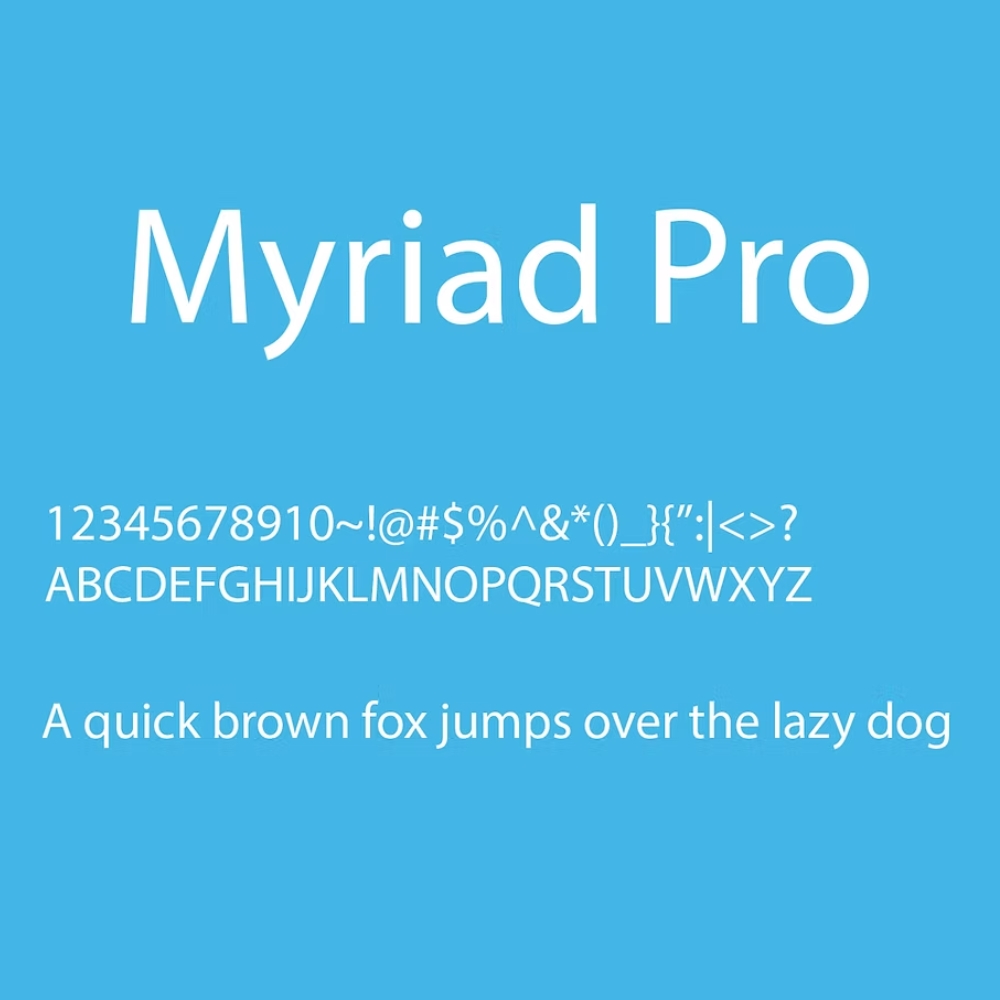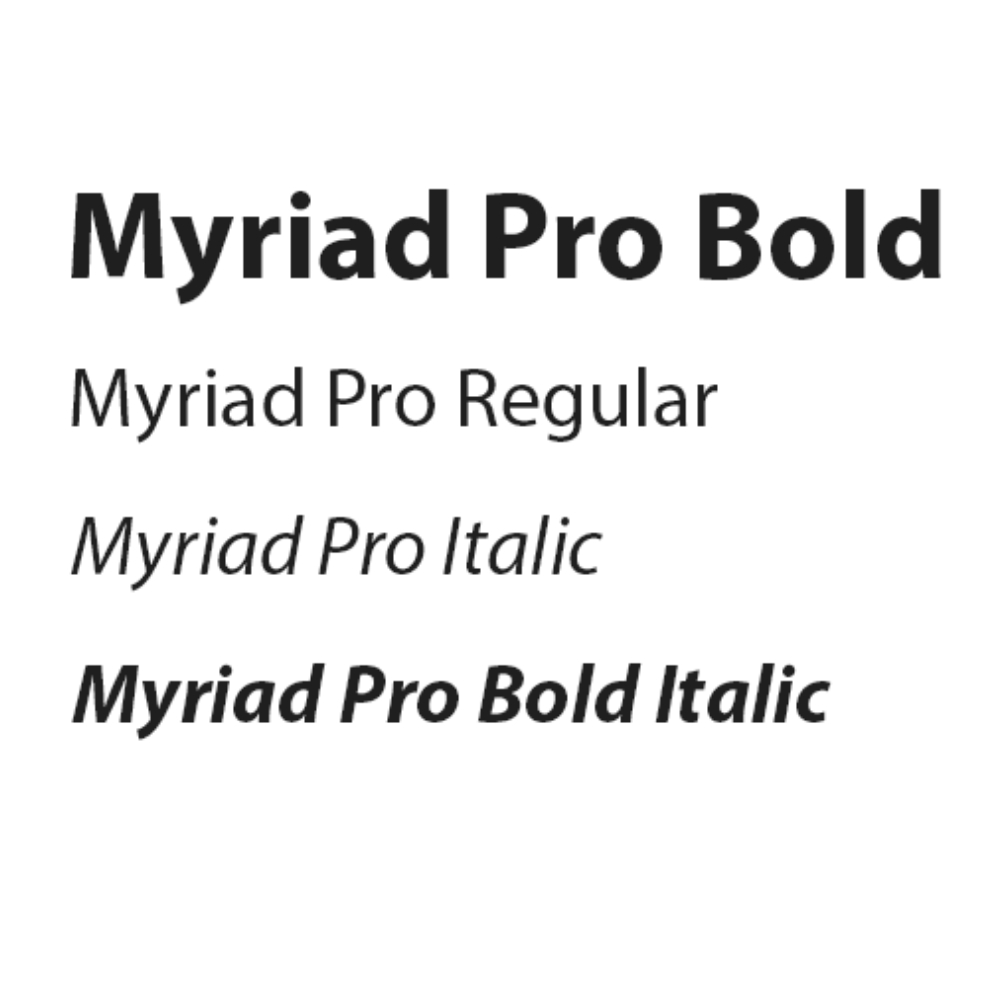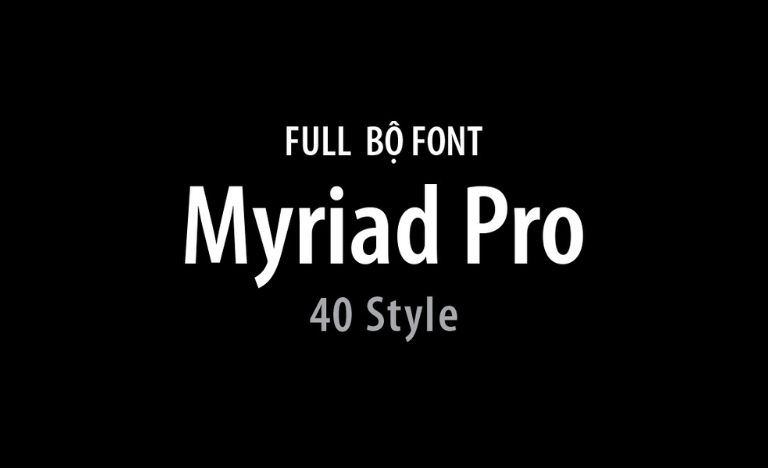
Tải 20+ font Myriad Pro chuyên nghiệp cho thiết kế
Myriad Pro là một trong những bộ phông chữ Sans-serif hiện đại được sử dụng rộng rãi nhờ cấu trúc cân đối, sạch sẽ và đầy tính chuyên nghiệp. Sự phổ biến của bộ font này đến từ khả năng hiển thị rõ nét trên cả các ấn phẩm in ấn lẫn giao diện kỹ thuật số. Việc download font Myriad Pro giúp các nhà thiết kế và kiến trúc sư tại Việt Nam có thêm phương án trình bày hồ sơ kỹ thuật, bản vẽ phối cảnh và bộ nhận diện thương hiệu một cách chỉn chu, hạn chế tình trạng lỗi hiển thị dấu tiếng Việt.
Khám phá những đặc điểm thẩm mỹ của dòng font Myriad Pro Việt hóa
Điểm thu hút của Myriad Pro nằm ở thiết kế Humanist Sans-serif với các đường nét mở, mang lại cảm giác thân thiện nhưng vẫn rất nghiêm túc. Khác với những phông chữ không chân thông thường, Myriad Pro sở hữu cấu trúc ký tự được tính toán kỹ lưỡng về khoảng cách, giúp văn bản trở nên thông thoáng và dễ tiếp nhận. Phiên bản download font Myriad Pro Việt hóa đã xử lý tinh tế hệ thống dấu thanh, đảm bảo tính đồng nhất về mặt hình học so với bộ chữ gốc, giúp bản thiết kế giữ được vẻ đẹp hiện đại xuyên suốt các trang tài liệu.
Sự ổn định của Myriad Pro còn được thể hiện qua dải biến thể phong phú. Với hàng chục kiểu chữ từ nét mảnh đến nét siêu đậm, người dùng có thể dễ dàng phân cấp thông tin một cách khoa học. Đây là lựa chọn phù hợp cho các dự án yêu cầu sự minh bạch, hiện đại như các bản thuyết minh dự án nhà lắp ghép, văn phòng container hay các tài liệu giới thiệu giải pháp xây dựng thông minh.
Phân loại phong cách Humanist Sans-serif / Modern Style
Các kiểu chữ tiêu biểu Regular, Bold, Italic, Condensed, SemiBold
Mục đích phù hợp Bản vẽ CAD, Hồ sơ năng lực, Branding, Website
Tư vấn lựa chọn: Myriad Pro phát huy hiệu quả thị giác cao khi bạn phối hợp các độ đậm khác nhau trong cùng một bố cục. Bạn nên download font Myriad Pro Bold cho các tiêu đề chính để tạo độ nhấn và dùng kiểu Regular cho phần nội dung mô tả chi tiết để đảm bảo tính dễ đọc cho hồ sơ dự án.
03 Ứng dụng font Myriad Pro vào thực tế kiến trúc
Nhờ vẻ ngoài khoa học và sự rõ ràng trong cấu trúc nét, việc sử dụng tải font Myriad Pro mang lại giá trị thực tế cao trong khâu vận hành và quảng bá công trình:
• Hệ thống biển hiệu văn phòng container: Những nét chữ hiện đại của Myriad Pro rất ăn ý khi được cắt chữ nổi mica hoặc dán decal tại các khu vực sảnh chờ, phòng họp. Phông chữ này giúp không gian toát lên vẻ chuyên nghiệp và tinh tế.
• Ghi chú kỹ thuật trên bản vẽ AutoCAD: Độ rõ nét của phông chữ giúp các thông số về vật liệu panel, kết cấu thép hay chi tiết lắp ghép trở nên dễ đọc, hỗ trợ đội ngũ giám sát triển khai công việc tại hiện trường hiệu quả hơn.
• Thiết kế hồ sơ năng lực: Sử dụng tải font Myriad Pro Việt hóa giúp trình bày thông tin năng lực thi công một cách mạch lạc, tạo ấn tượng về một đơn vị có quy trình làm việc bài bản và tư duy thẩm mỹ hiện đại.
03 Lưu ý bố cục hồ sơ thiết kế với font Myriad Pro chỉn chu
Để khai thác hiệu quả vẻ đẹp của dòng font Sans-serif đa năng này mà không gây cảm giác đơn điệu, người thiết kế nên lưu tâm một số lưu ý kỹ thuật sau:
• Kiểm soát khoảng cách dòng: Với cấu trúc chữ hiện đại, bạn nên để khoảng cách dòng thoáng một chút (khoảng 1.4 lần cỡ chữ) để văn bản không bị bết dính, giúp người đọc cảm thấy thoải mái hơn khi tiếp nhận các thuyết minh dự án dài.
• Sử dụng biến thể Condensed hợp lý: Trong các bảng thống kê vật liệu xây dựng có nhiều cột số liệu, việc sử dụng Myriad Pro Condensed là phương án tối ưu để hiển thị đầy đủ thông tin mà không cần giảm kích thước chữ quá nhỏ.
• Tính đồng bộ xuyên suốt: Hãy duy trì sử dụng Myriad Pro từ bản vẽ thiết kế đến slide trình chiếu và báo giá gửi khách hàng. Sự nhất quán về kiểu chữ giúp hình ảnh thương hiệu của bạn trông uy tín và chuyên nghiệp hơn.